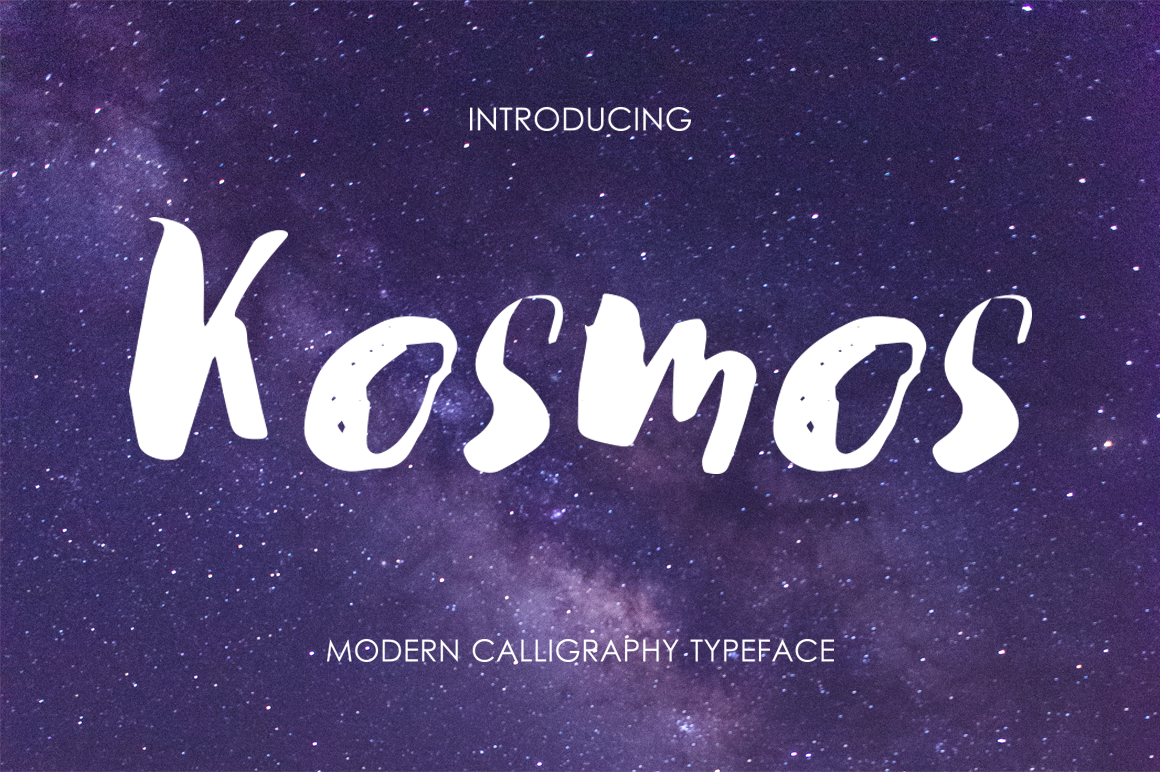
A Kosmos Brush Font é uma opção elegante para designers que procuram texturas únicas e modernas para seus projetos visuais. Desenhada pelo designer 178-MC, esta fonte premium está disponível gratuitamente de hoje em CreativeMarket. KOSMOS não é apenas um tipo casual; é uma mistura única entre grunge e contemporâneo que se destaca por sua versatilidade. Este tipo é perfeito para aplicação em cartões de casamento, convites sociais, cards de baias, menus de eventos, logotipos, tags de promoção, personalização de endereços e até mesmo embalagens. Seu estilo moderno e arredondado cria um enquadramento sofisticado, enquanto sua textura irregular evoca sentimentos de grunge e desenho livre. Com KOSMOS, os designers têm à disposição uma fonte versátil para criar design único em uma variedade de formatos. É o tipo perfeito para quem busca algo que combine elegância com um toque deslavado, tornando a Kosmos Brush Font uma opção ideal tanto para projetos profissionais quanto para aqueles que valorizam uma paleta de personalização e criatividade.